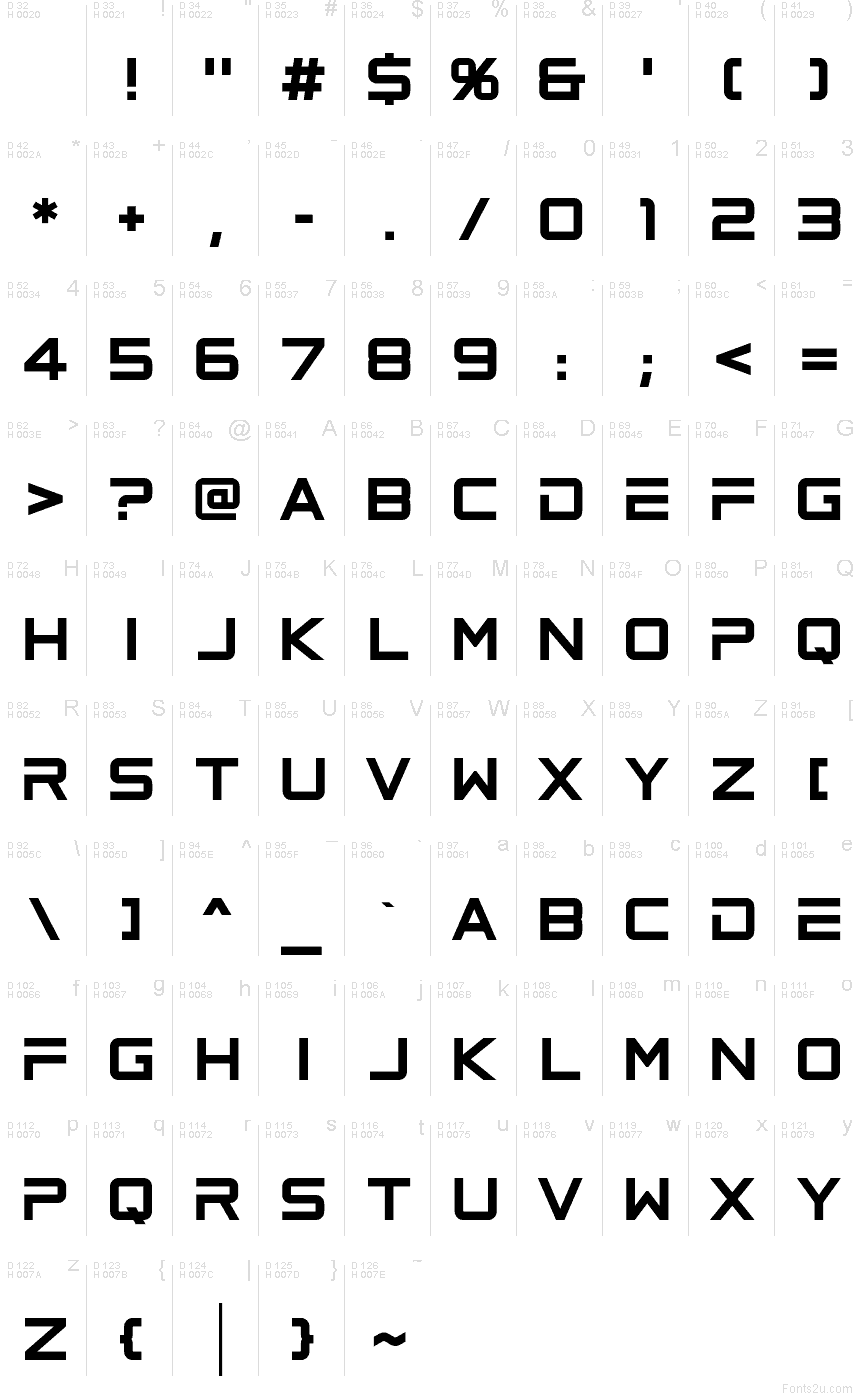
Horyzen Title Bold, zaprojektowany przez LyonsType, to darmowy, futurystyczny font typu display o wyrazistym, technologicznym charakterze. Litery zbudowane są z szerokich, geometrycznych pociągnięć, łączących kwadratowe formy zewnętrzne z zaokrąglonymi łukami wewnątrz. To połączenie nadaje fontowi elegancki, zaprojektowany rytm, daleki od chłodnej, cyfrowej surowości.
Sprawdza się świetnie na plakatach, w brandingu gier, grafikach na eventy technologiczne, okładkach albumów czy w tytułach, gdzie krótkie słowa wymagają zwartej, dynamicznej formy. Jako darmowy font, doskonale nadaje się także do logotypów, nagłówków i monogramów, ponieważ ścięte kąty oraz szerokie, stabilne kształty nadają nawet kilku literom silną, graficzną prezencję.
Kroje pisma bazujące na wielu logotypach procesorów i produktów AMD Ryzen.
Zaktualizowano literę „Z” w odmianie Bold na podstawie ZenDNN.
Zaktualizowano cyfrę „4” oraz literę „x” w odmianie Bold na podstawie CDNA 4 i CDNA Next.
Wprowadzono drobne zmiany w kilku glifach i dodano alternatywy stylistyczne do Horyzen Digital.
Horyzen Digital przemianowano na Horyzen Title. Wprowadzono dodatkowe zmiany w tym kroju oraz w pozostałej części rodziny fontów.